Anhand ausgewählter Werke aus der Ausstellung beleuchtet sie die unterschiedlichen Traditionen
der ostasiatischen und europäischen Kalligrafie. Während in Ostasien Schrift häufig als Bild und
Ausdruck des Augenblicks verstanden wird, steht im Westen die Gestaltung der Schrift
als Träger von Sprache und Kultur im Mittelpunkt. Der Vortrag eröffnet neue Perspektiven
als schöne Schrift zu entdecken – als sichtbaren Ausdruck von Kultur, Persönlichkeit und Zeit.
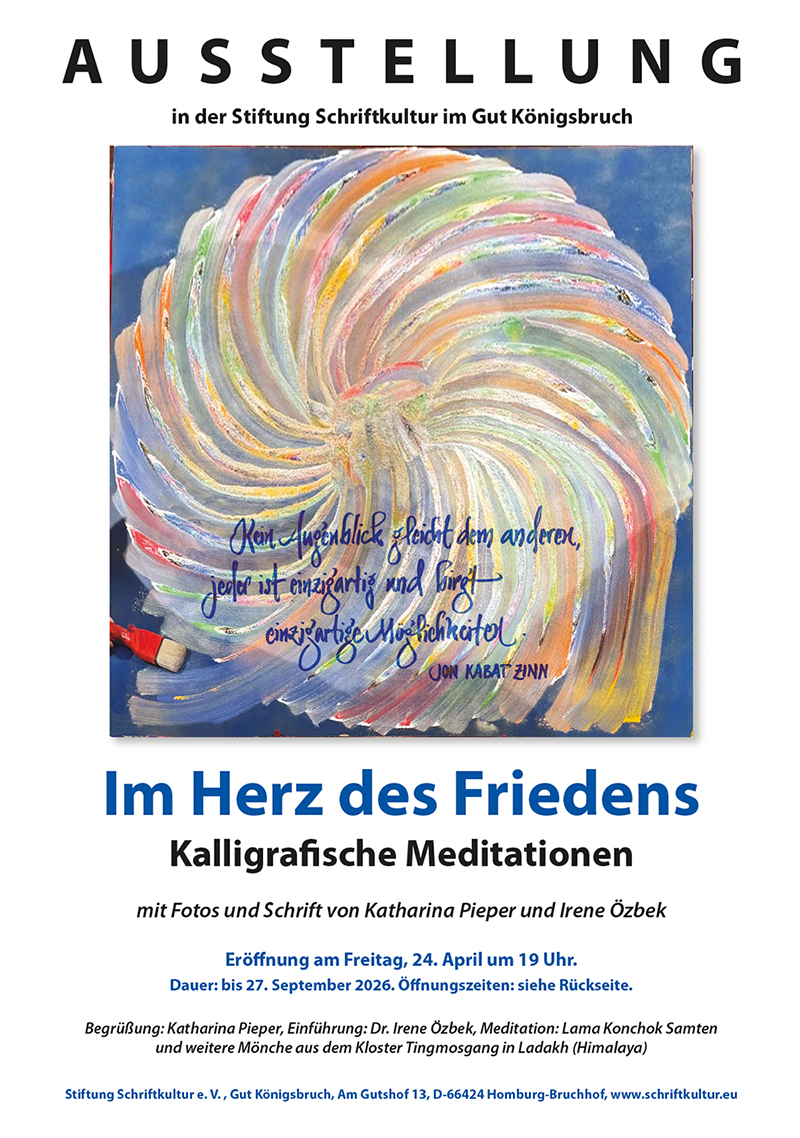
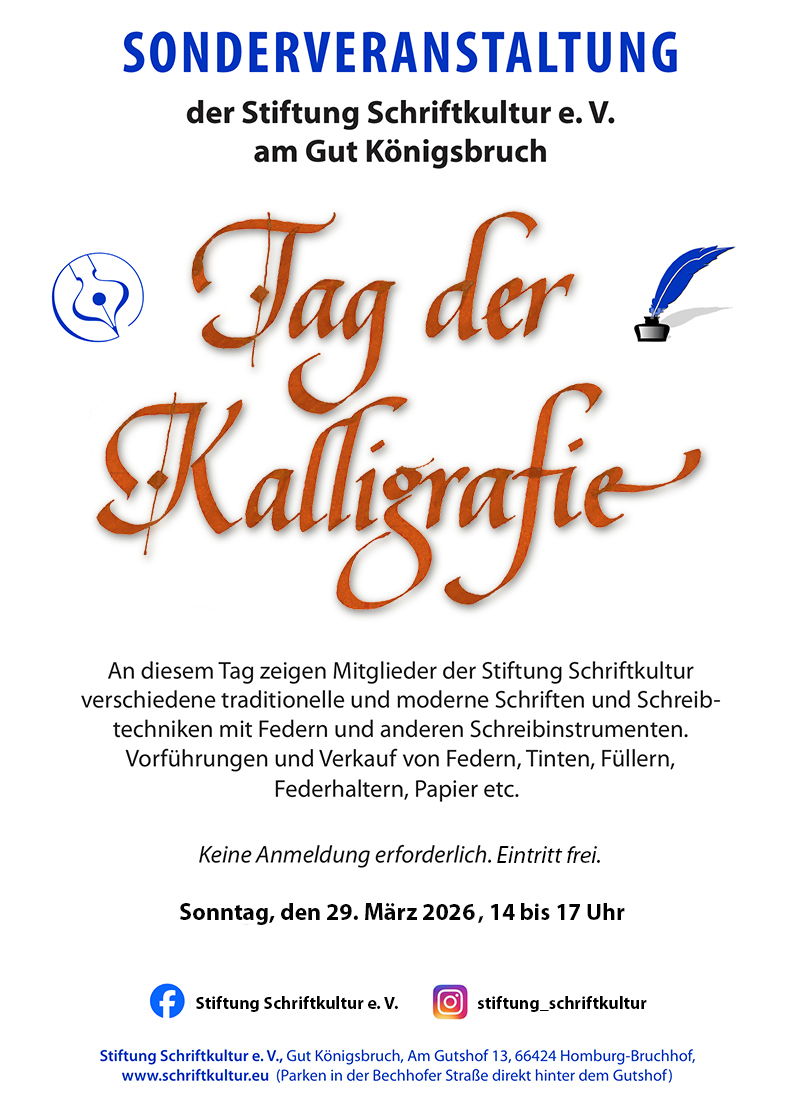
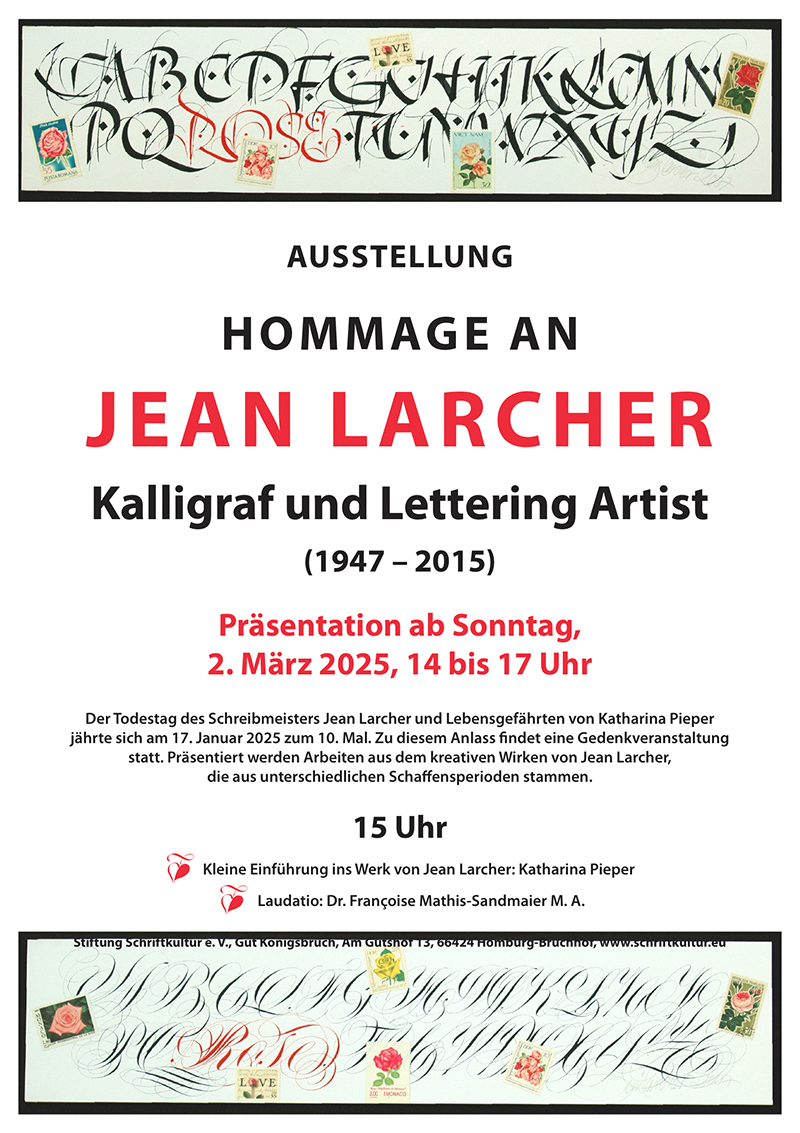
Die Ausstellung „Hommage an Jean Larcher – Kalligraf und Lettering Artist 1947 - 2015“
kann an diesem Tag ebenfalls angesehen werden. Arbeiten aus seinem kreativem Schaffen,
die bisher erst selten gezeigt wurden, sind in dieser Ausstellung in einem kleinen Überblick präsentiert.
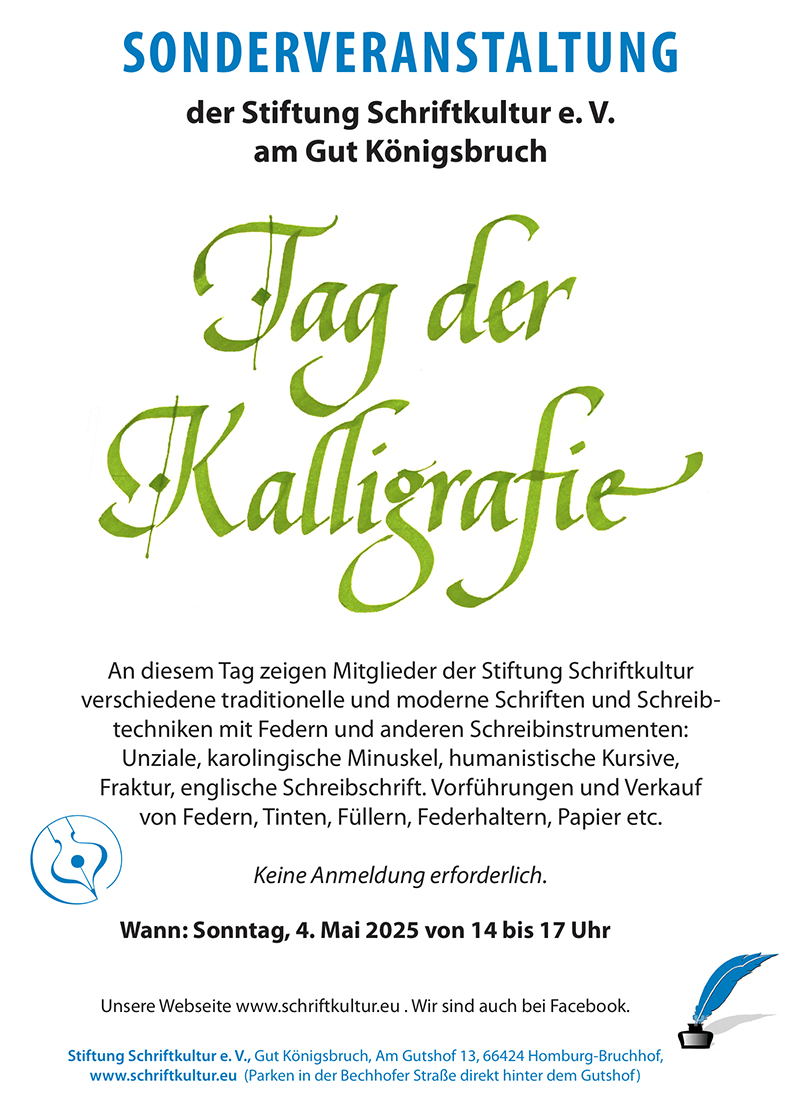
- Exkursionen
Unsere allgemeinen Termine im Gut Königsbruch werden auch in der lokalen Presse bekannt gegeben